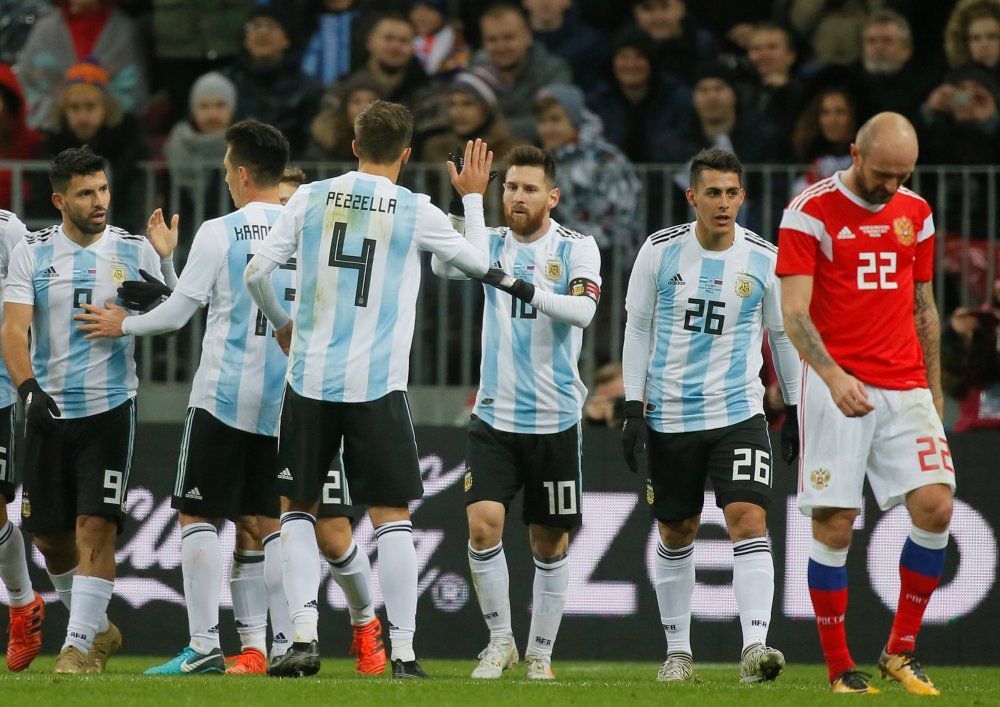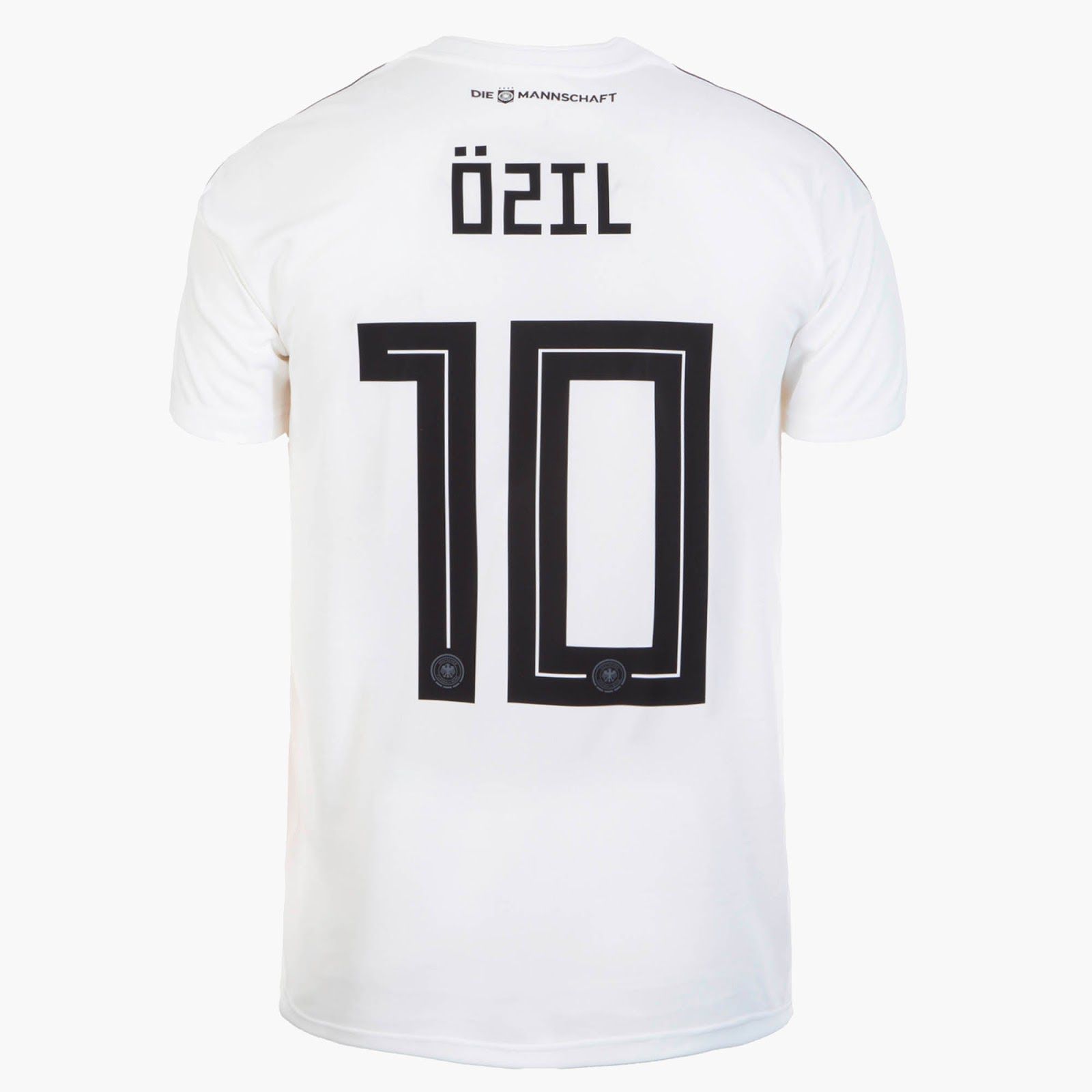
Il font di adidas per i Mondiali 2018 ha un problema Diciamo il problema peggiore che può capitare ad un font: non si legge
AGGIORNAMENTO: dopo una settimana esatta daall'inizio dei Mondiali, molti utenti di Twitter hanno criticato pesantemente il font di adidas, ecco qualche esempio.
Quali sono le qualità che un font per una maglietta da calcio deve avere? Deve essere stiloso, attenersi alle miriade di regole della FIFA su grandezza e visibilità e - last but not fo least - deve essere comprensibile. Ecco il font creato da adidas per le maglie delle Nazionali che andranno in Russia a giocare il Mondiale 2018 sembra soddisfare i primi due criteri, ma non il più importante cioè l'ultimo. Su Twitter è cirolata molto la foto della maglia della Germania di Julian Draxler, il cui cognome sembra prestarsi a varie interpretazione a causa delle forme squadrate del design.
Il font di adidas per il Mondiale ha uno stile futurista e spigoloso, ispirato all'alfabeto cirillico e all'immaginario sovietico degli anni '. Le forme delle lettere e i numeri non hanno curve, solo angoli a 90 gradi (con tre eccezioni: la X, la V e la Z). Una linea passa nel mezzo dei numeri, riducendo un po' il "peso" della figura, mentre le lettere rimangono piene. Il problema di leggibilità è causato proprio dagli spigoli nelle lettere: la X, la H, la R, la K, la A, la D e la O si confondono clamorosamente, mentre la Z è identica al numero 2.
Cosa farà adidas a questo punto? Niente probabilmente, ma sono questi dettagli - insieme ad esempio alla qualità degli shooting per la prensetazione delle maglie - a mostrare la distanza con il suo competitor più importante, la Nike.